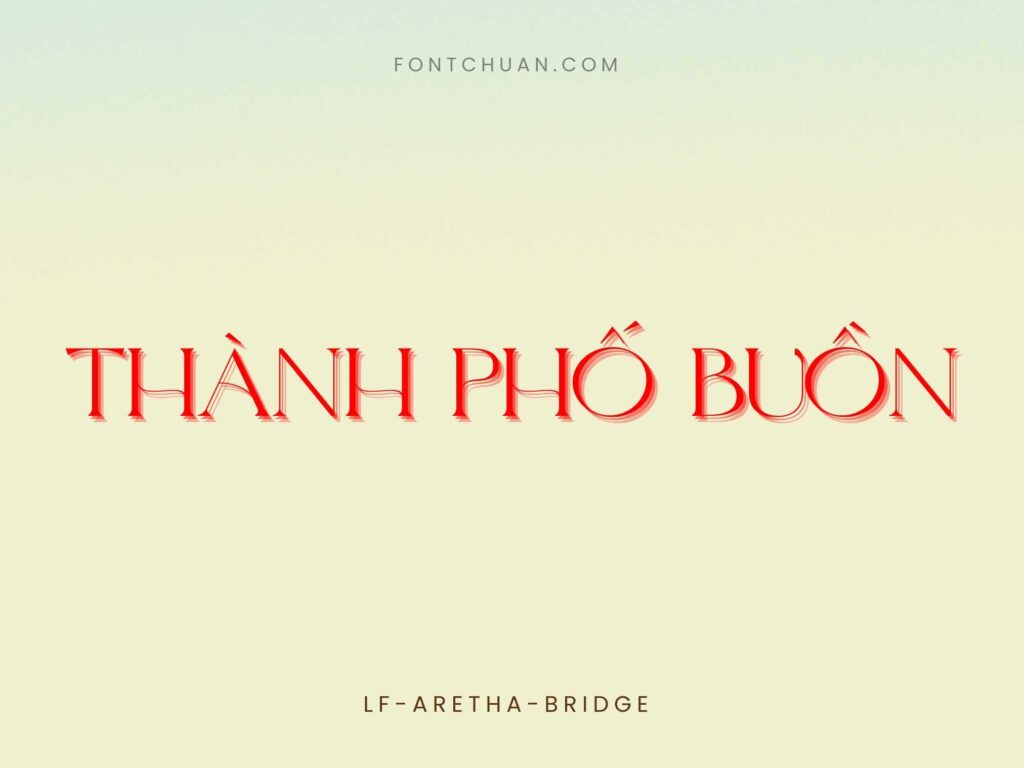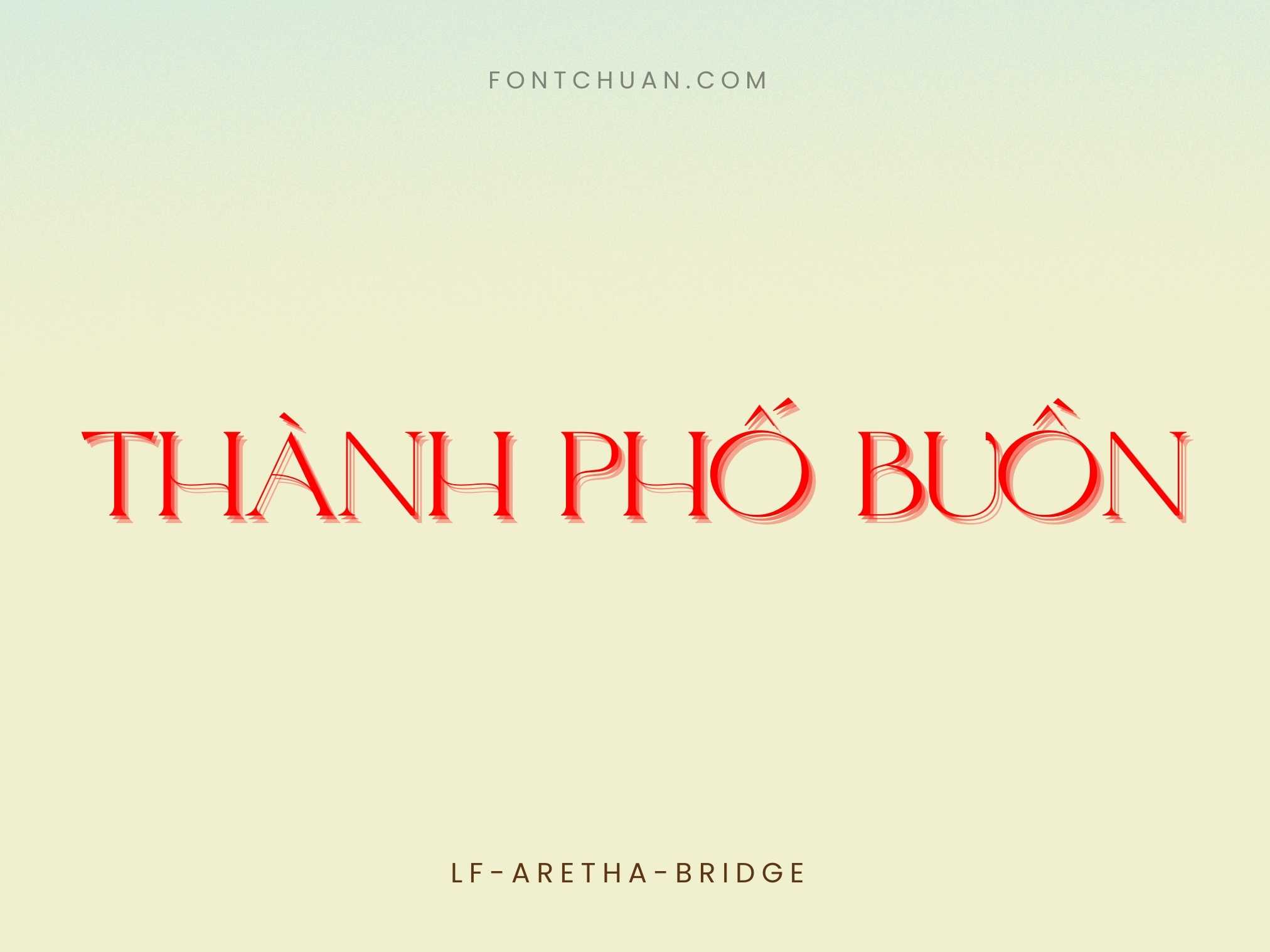
Font Lf Aretha Bridge Việt Hóa
Aretha Bridge là một phông chữ serif hiện đại và thanh lịch, được thiết kế bởi 177Studio. Phông chữ này mang lại sự tinh tế và độc đáo cho các dự án thiết kế, phù hợp với nhiều mục đích sử dụng khác nhau. Aretha Bridge hỗ trợ đa ngôn ngữ, bao gồm cả tiếng Việt, giúp mở rộng khả năng ứng dụng trong các dự án quốc tế. Phông chữ này đã được thành viên của Font Chuẩn lựa chọn và sưu tầm, đáp ứng nhu cầu của bạn đọc và ứng dụng thực tế vào các dự án thiết kế.
Về đặc điểm thiết kế, Aretha Bridge sở hữu các đường nét thanh mảnh, tinh tế với các ligature độc đáo, tạo nên sự mềm mại và uyển chuyển trong từng ký tự. Phông chữ này phù hợp cho các ứng dụng như thiết kế logo, tiêu đề, thương hiệu lấy cảm hứng cổ điển, biển hiệu và các dự án sáng tạo khác. Ngoài ra, Aretha Bridge còn có thể được sử dụng như một Font chữ công nghệ, lý tưởng cho các thiết kế liên quan đến giao diện số, tài liệu kỹ thuật, website và các sản phẩm công nghệ, mang lại vẻ hiện đại và chuyên nghiệp.
Ngoài ra, cho những thiết kế mang không khí lễ hội, vui nhộn, Aretha Bridge cũng là một lựa chọn Font chữ Halloween hoàn hảo với các họa tiết đặc trưng như mạng nhện, dơi và bóng ma, tạo điểm nhấn sôi động cho các sự kiện như lễ hội, sinh nhật, ngày Nhà giáo và Valentine, mang lại sự khác biệt nổi bật so với các font cổ điển như Aretha Bridge.